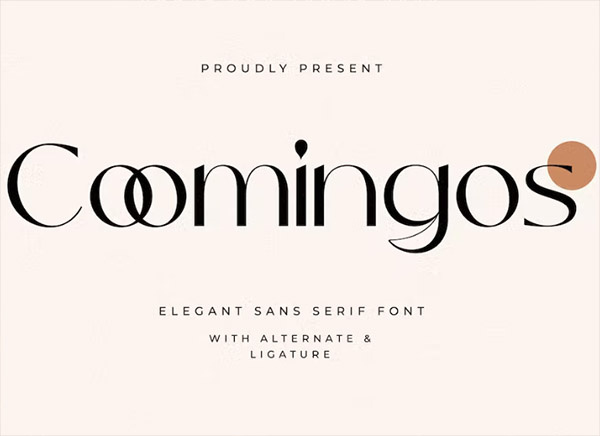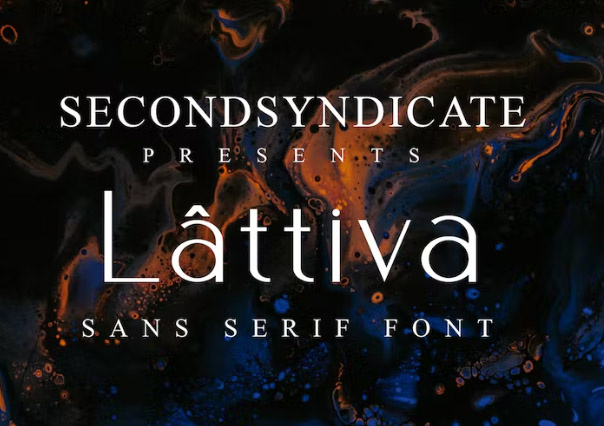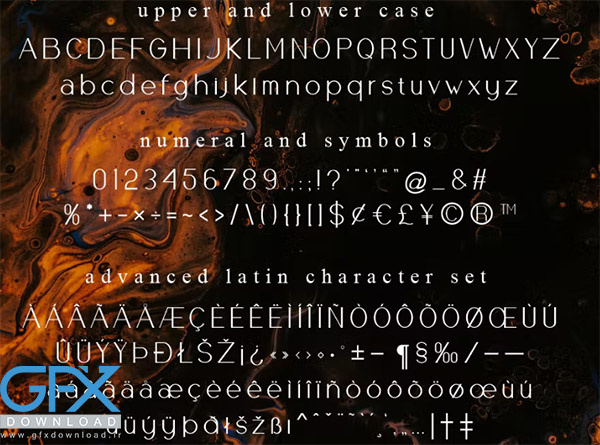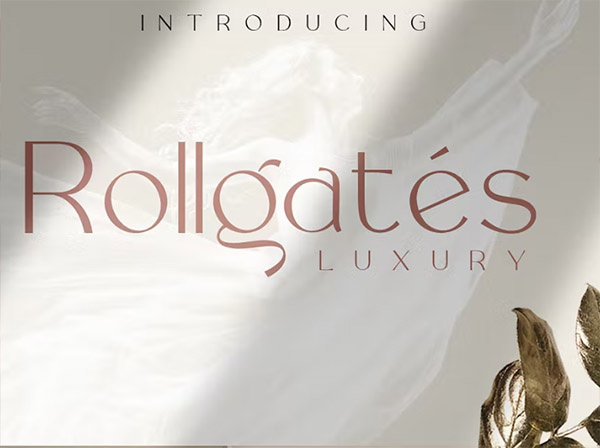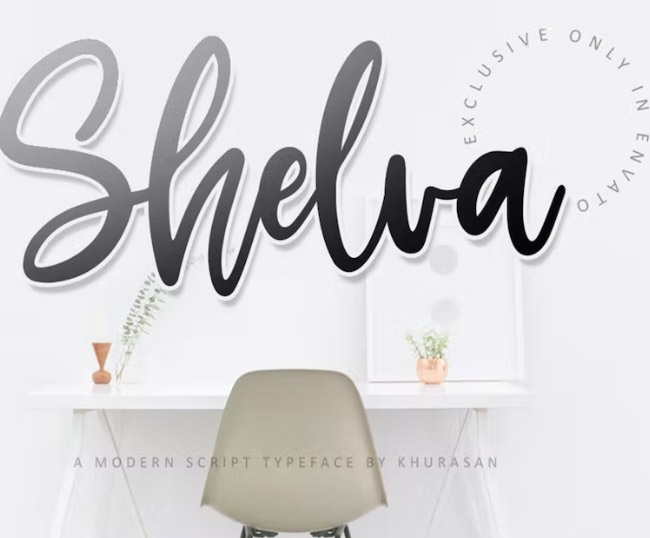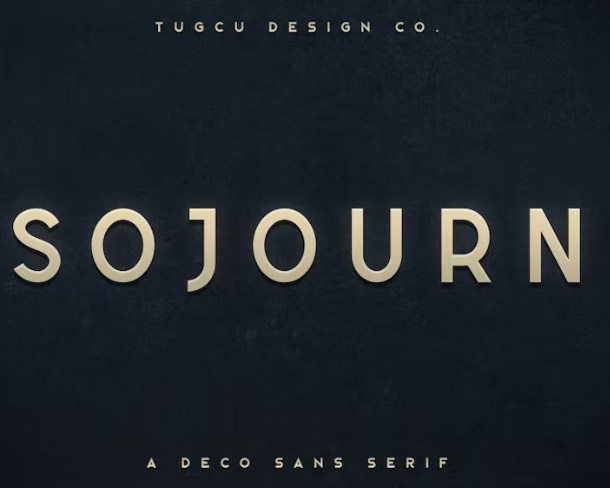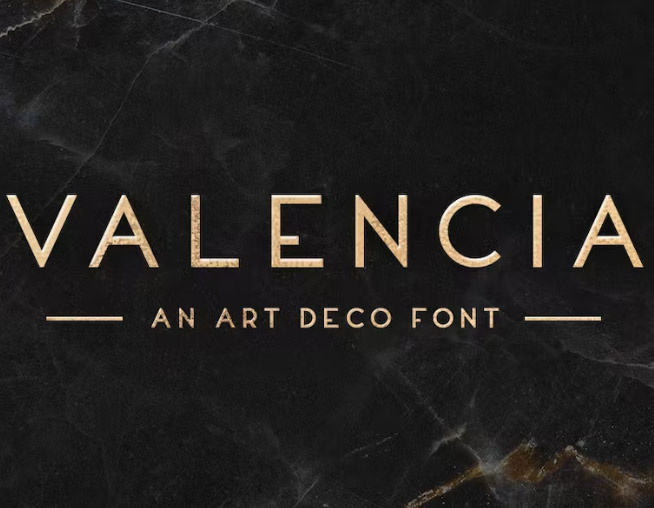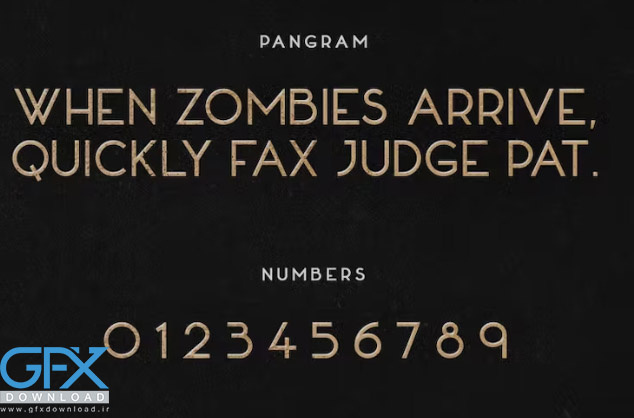
دانلود بهترین فونت ها برای طراحی پاورپوینت
بهترین فونت ها برای طراحی پاورپوینت
دانلود مجموعه بهترین فونت ها برای طراحی پاورپوینت
در این پست با مجموعه ای از زیباترین فونت ها برای طراحی پاورپوینت که با استفاده از آن ها می توانید فونت پاورپوینت خودتون رو تغییر بدین با شما هستیم. شما می‌توانید از آن‌ها در هنگام تایپ مطالب خود در نرم افزارهای نوشتاری مانند ورد و پاورپوینت استفاده نمایید. این مجموعه شامل 7 فونت زیبا و چندمنظوره برای نرم افزار پاورپوینت می باشد. با دانلود بهترین فونت ها برای طراحی پاورپوینت می‌توانید از آنها در قالب‌های پاورپوینت خود استفاده کرده تا به پاورپوینت شما زیبایی دو چندان ببخشید. در این مجموعه بهترین فونت برای پاورپوینت در اختیاز شما قرار گرفته شده است چرا که لازمه یک قالب حرفه‌ای رعایت اصول نگارشی، داشتن ابتدا و انتهای مشخص، استفاده از فونت مناسب و استاندارد می‌باشد.
فونت انگلیسی برای پاورپوینت Valencia
Valencia یک فونت زیبا و کاربردی برای طراحی پاورپوینت است. این فونت با نمایش هندسی به همراه حروف بزرگ چند زبانه، اعداد و علائم نگارشی است.
فونت انگلیسی برای پاورپوینت
Lattiva این فونت با طراحی چنرمنظوره مناسب برای اهداف شخصی یا تجاری شما می باشد. فونت انگلیسی برای پاورپوینت با فرمت های (OTF، TTF، WOFF) ارائه شده است.
بهترین فونت پاورپوینت Coomingos
یک فونت sans serif زیبا و مدرن است. بدون توجه به موضوع، این فونت یک پکیج باورنکردنی برای کتابخانه فونت‌های شما خواهد بود، زیرا این قابلیت را دارد که هر خلاقیتی را ارتقا دهد. شامل حروف بزرگ – کوچک – نمادها و علائم نقطه گذاری – اعداد – لیگاتور – جایگزین – پشتیبانی چند زبانه. با فرمت های (OTF، TTF، WOFF، WOFF2) ارائه شده است.
بهترین فونت برای پاورپوینت پایان نامه
Sojourn یک فونت نمایشی زیبا با حروف بزرگ چند زبانه، اعداد و علائم نگارشی است. نسخه Webfont نیز گنجانده شده است. یکی از بهترین فونت های انگلیسی برای پاورپوینت پایان نامه، سمینار، پروپوزال و غیره می باشد.
فونت دستخط برای طراحی پاورپوینت
Better Step نام این فونت زیبا برای طراحی پاورپوینت با سبک دست خط و دست نویس می باشد. یک فونت با کاراکتر های خیره کننده است. ساخته شده با براش و جوهر پایه آب با کیفیت بالا. ایده آل برای برچسب نام، نقل قول های دست نویس، بسته بندی محصول، کالا، رسانه های اجتماعی، کارت های تبریک، و غیره. این شامل مجموعه کاملی از حروف کوچک و بزرگ، طیف وسیعی از علائم نگارشی، اعداد است. شامل فایل های Otf - Ttf و Webfonts
فونت لاکچری طراحی پاورپوینت Rollgates Luxury
یک فونت پر زرق و برق دار است که هم به لحاظ کلاسیک ظریف و هم مدرن است. برای دعوت نامه های عروسی، چیدمان مجل و هر گرافیکی که نیاز به ظاهری براق با استعدادی قدیمی دارد، استفاده کنید. شامل کاراکترهای بزرگ ، کاراکترهای کوچک - پشتیبانی چند زبانه برای زبان های مختلف از جمله: فرانسوی، آلمانی، اسپانیایی، پرتغالی، ایتالیایی، هلندی، فنلاندی، سوئدی و غیره.
فونت برای پاورپوینت Shilva
Shilva یک فونت سرگرم کننده، سبک تازه و مدرن است. مناسب برای لوگو، برندینگ، کارت تبریک، پوستر و هر طرحی که ایجاد می کنید. شامل فایل های Shilva Script.ttf و Shilva Script.otf
بهترین فونت‌های پاورپوینت برای ارائه